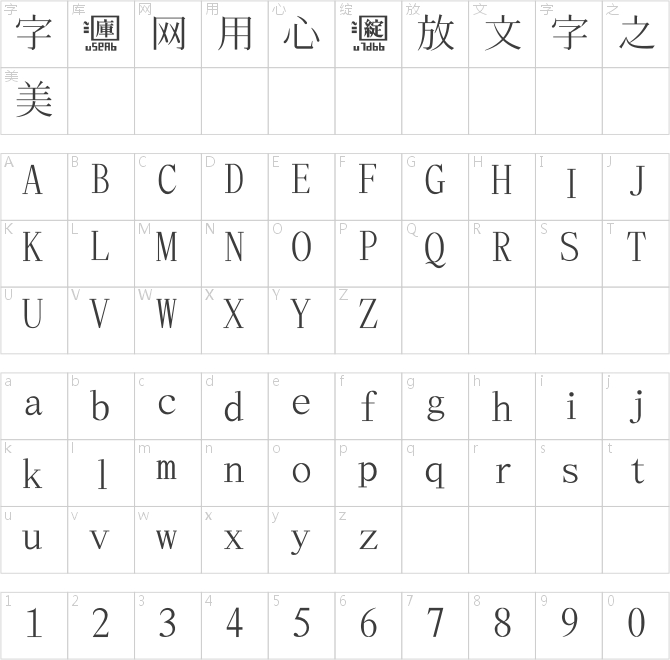
字体名称: 香港民间字集
香港民间字集
香港民间字集介绍
香港民间字集字体下载HKCS Traditional Orthography
香港民间字集(HKCS)是一项在明代字体中创建现代和历史汉字字体目录的项目。这是一种支持传统正字法的衬线字体,它是由@SyaoanHinata所勾画的。传统的正字法是比较适合现代甲骨文、青铜铭文和小印章词源研究的。此版本的字体包括Uro/Uro+中的所有字符,并从分机A/B中选择字符,以便在香港支持粤语。